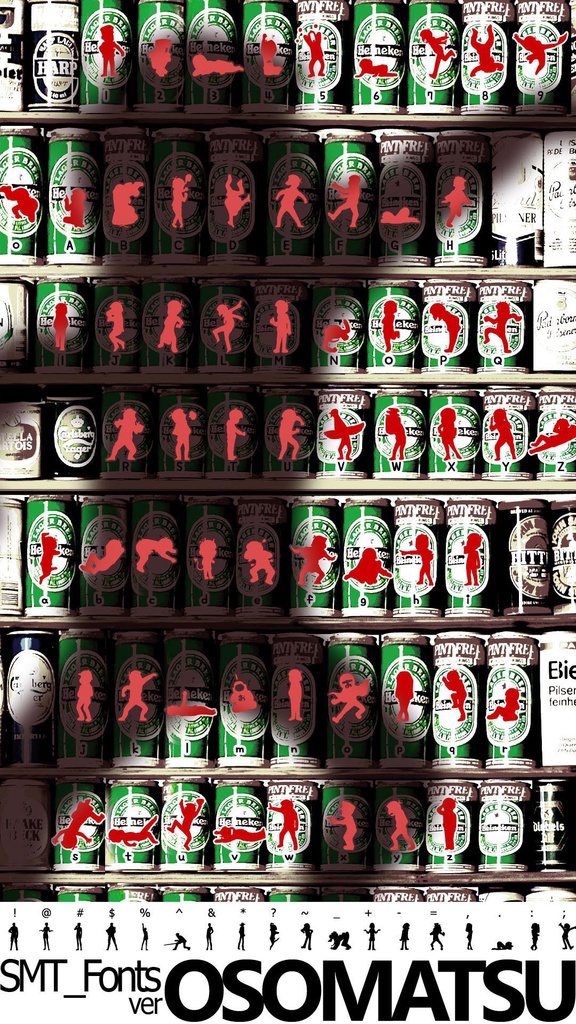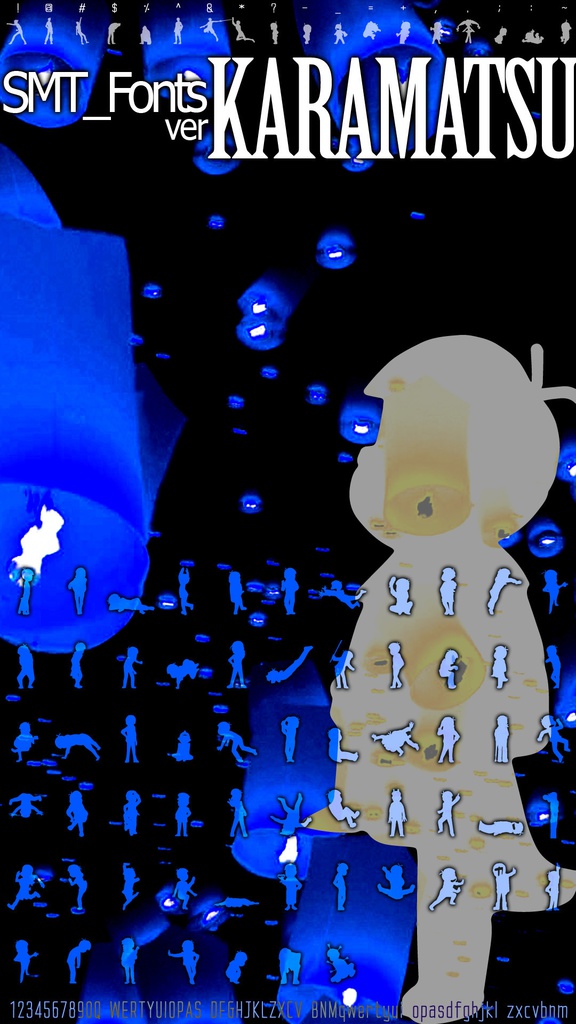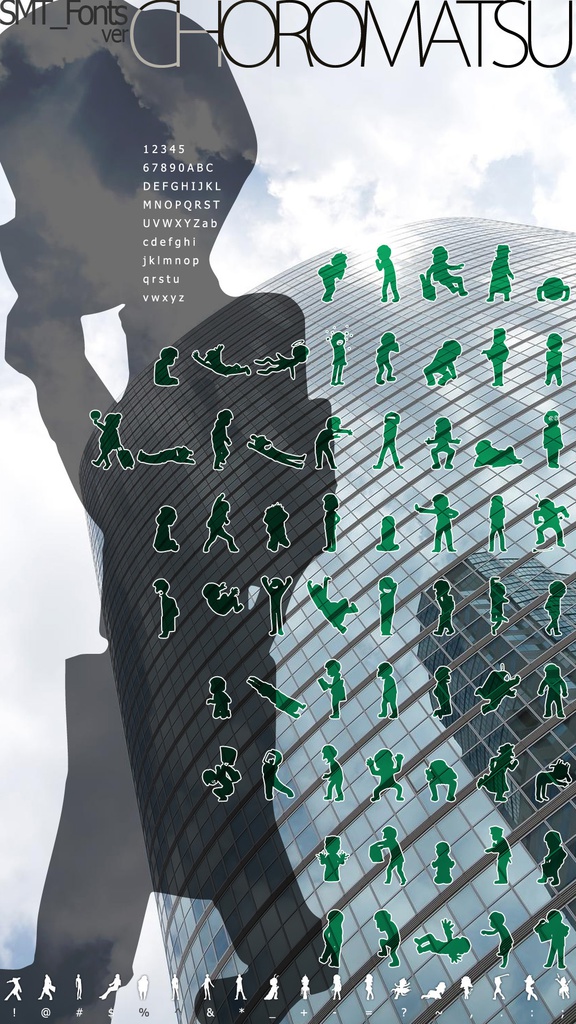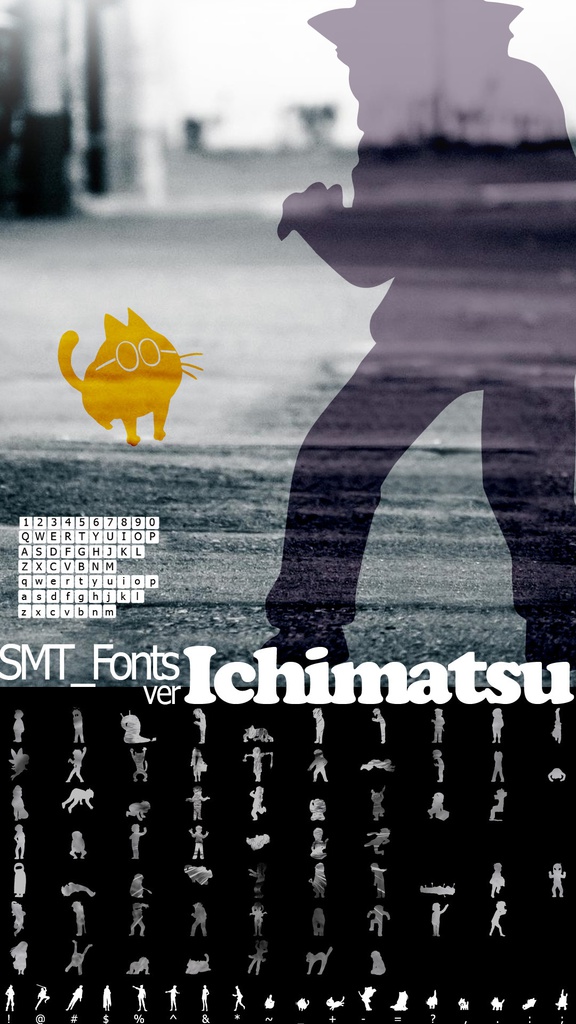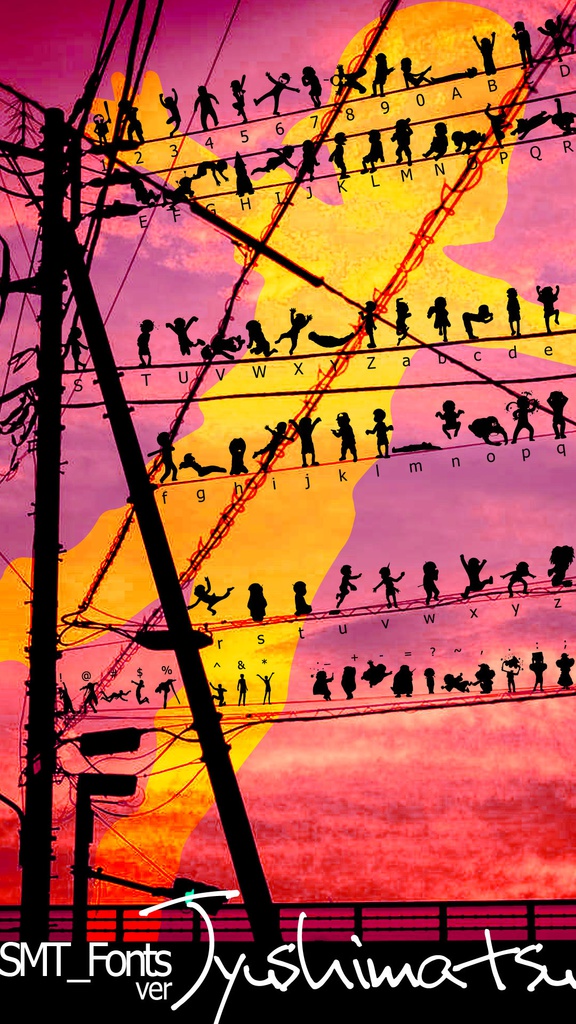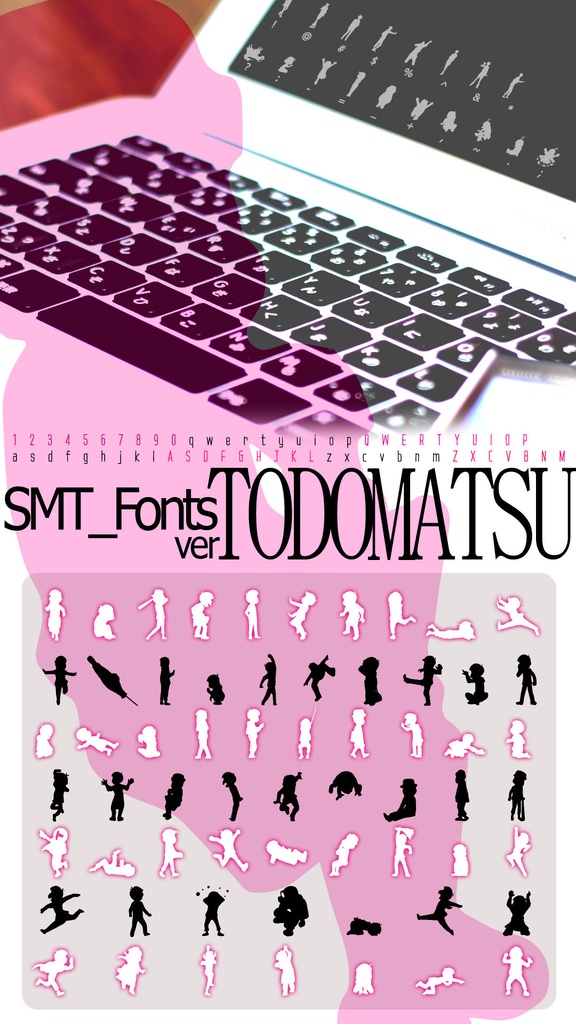
SMT_fonts
絵文字風フォントを、六つ子にさせても面白いのではないかという思いつきで勝手に作った非公式のフリーフォントです。トレスして、シルエットにしてベクター化しただけのものです。 OpenTypeのフォントです。ひとまずWin7/Macで使えるようにはなっていると思います。 動作確認も含め、すごく粗末なできのものになりましたので、名前はSMT_fontsとつけました。そまつふぉんつと呼んでください。 対応している文字は、下記のとおりとなります。 1234567890 ABCDEFGHIJKLMNOPQRSTUVWXYZ abcdefghijklmnopqrstuvwxyz !@#$%^&*?~-_=+,.;: フリーフォントですので、使用時の連絡不要・製作者の表記不要・加工OKです。動画の素材や表紙、イラストの背景などなど、粗末なものですが、どうか楽しんで使っていただければ幸いです。 ただし、商用に使用した時のいかなる被害及びトラブルについて、製作者は一切の責任を負いかねます。何卒ご了承ください。 フォントの使用に関して不都合等がありましたら、是非こちらのメッセージかabies.uster@gmail.comのほうにご連絡ください。 ※製作者は、公式様とは一切関係ありません。